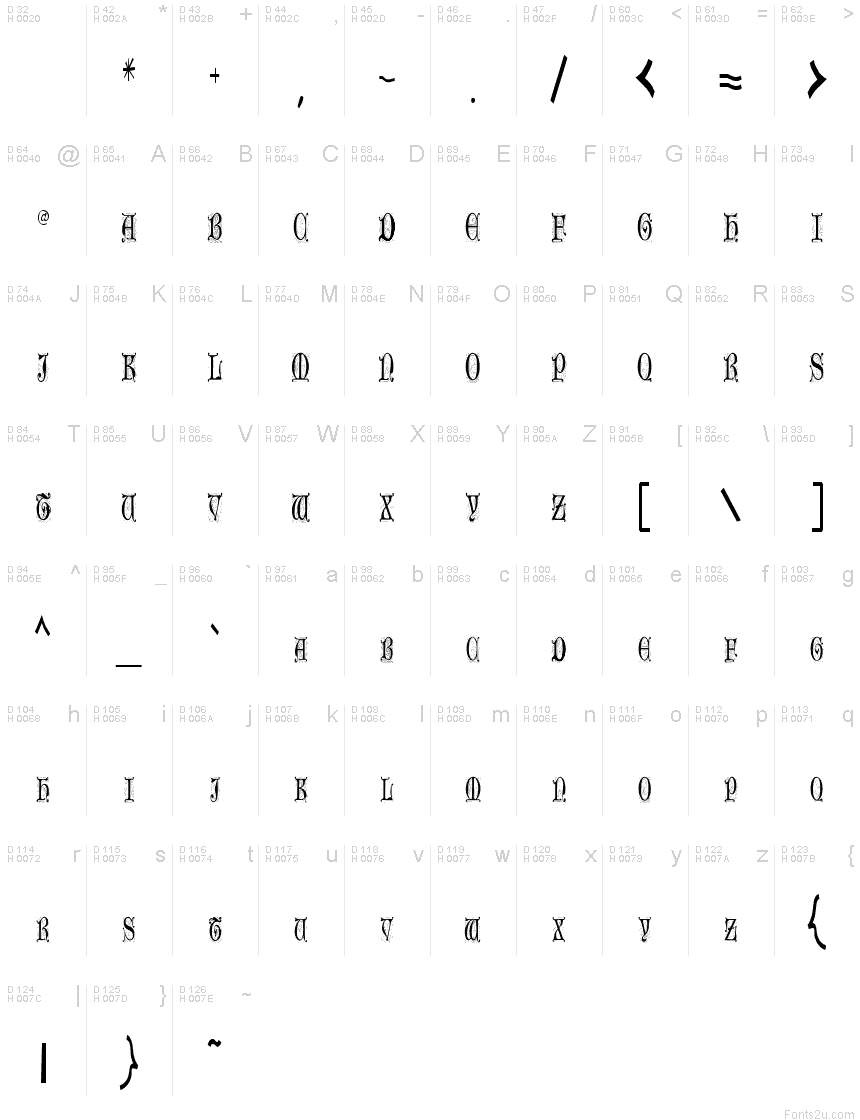
Older autorstwa Me to darmowy, ozdobny, średniowieczny krój gotycki. Każda litera jest ujęta w głębokie, czarne kontury i wypełniona delikatnymi grawerunkami przypominającymi pnącza, co nadaje jej wygląd ręcznie rzeźbionego drewna lub iluminowanego rękopisu. Rytm pisma jest wyrazisty, a zarazem misterny, dzięki czemu nawet pojedyncze słowo w Older natychmiast nabiera starożytnego, ceremonialnego i nieco tajemniczego charakteru.
Z Older tytuły i logotypy do powieści fantasy, sesji RPG, wydarzeń tematycznych, jarmarków renesansowych, etykiet vintage czy plakatów w klimacie okultystycznym zyskują bogatą, bajkową atmosferę niemal bez dodatkowej pracy projektowej. Ten darmowy font najlepiej sprawdza się w dużych rozmiarach, w których wewnętrzne zdobienia mogą „oddychać”; do tekstu towarzyszącego dobierz prosty, geometryczny krój bezszeryfowy, aby zachować czytelność i przejrzystość układu.